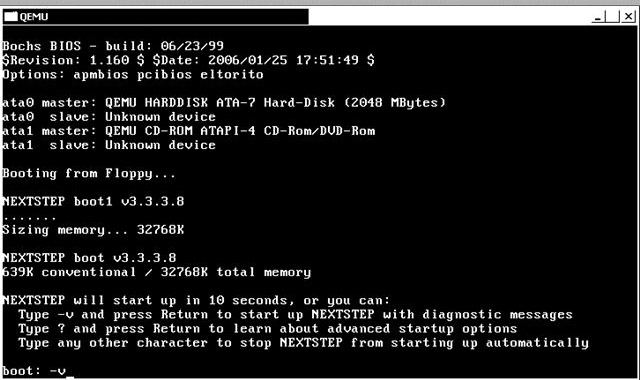
Systemschrift NeXT
Das Problem bei solchen vektorisierten Pixelschriften, dass die Pixel eben fast nie auf Bildschirmpixel fallen und durch fast immer fehlendes, und bei soler Schriftart recht kompliziertes Hinting dann auf dem Bildschirm grausam aussehen, werden sie nicht sehr groß dargestellt.
Das hier ist die Schrift der Oberfläche:
, ich suche jedoch eigentlich die Schrift, die bei einer kernel panic angezeigt wird wird bzw. beim Hochlaufen und Herunterfahren. Oder ist das bei Mac OS X vor Maverick immer noch die gleiche geblieben?
P.S.: Ich habe mal Mac OS X im »Verbose mode« hochgefahren. Es ist in der Tat dieselbe Pixelschrift, wie NeXT sie verwendet hat.
Ich fürchte, da wirst du kaum Erfolg haben.
In dem abgebildeten Terminal-fenster handelt es sich um eine 5 x 10 Pixel Schrift. In diesem Raster ist natürlich für eine lesbare Schrift nicht all zu viel Gestaltungs-Freiraum, daher wird die auch kaum einen Namen haben.
Generell sind Pixelfonts ja bei gringer Auflösung und auch einem Röhrenmonitor, der problemlos jede Auflösung darstellen kann ja unschlagbar. Bei LCD-Monitoren, die ja prinzipbedingt Pixel (aus je einem RGB-Tripel) besitzen, relativiert sich dieser Vorteil wieder deutlich, da ja hier eine niedrige Auflösung der System-Nur-Text-Ausgabe auf die Bildschirmpixel neu abgetastet werden müssen. Das übernimmt dann wieder ein Grafikprozessor auf dem Mainboard des Bildschirms, und die machen oft ziemlichen Murks aus einem Pixelfont, drum sind viele Betriebssysteme dazu übergegangen, auch bei Systemmeldungen (Bluescreen, Kernal-Panic, Ladebestätigungen für Softwaremudule und Gerätetreiber bei Linux) und in Terminal-/Eingabeaufforderungs-Fenstern auch Vektorschriften zu verwenden.
Zwar ist in Windows10 noch immer ein recht breites Sortiment an Pixelschriften installiert, in einer realen Anwendung habe ich sie jedoch nicht mehr gesehen. Möglich, dass hier das System den Bildschirm erkennt, und diese nur auf Röhrenbildschirmen nutzt.
Vektorisierte Pixelschriften sind jedoch ein Anachonismus, und sind außer in "Digital-historisierenden" Dokumenten praktisch schlechter in der Bildschirmdarstellung als Vektorfonts mit wenigen Ankern und glatten Konturen, die sich deutlich besser auf die native Bildschirmauflösung rendern lassen, Besonders, wenn anständige Hints zur Verfügung stehen.
Zwar ist in Windows10 noch immer ein recht breites Sortiment an Pixelschriften installiert, in einer realen Anwendung habe ich sie jedoch nicht mehr gesehen. Möglich, daß hier das System den Bildschirm erkennt, und diese nur auf Röhrenbildschirmen nutzt.
Wahrscheinlich sind diese nur deshalb noch installiert, damit falls ein älteres Programm danach verlangt sie noch vorhanden sind.
Ein älteres Programm wie z.B. das OS?
Also, das hier hier ist ein Foto vom Bootvorgang einer NeXT. Und *diese* Schrift habe ich gesucht.
@ catfonts: Es gibt keine »vektorisierten Pixelschriften.«. Die Entwicklung, war von Vektoren über Bézierkurven und dann idiotischerweise quadratische Q-Splines (TrueType).
Ich gebe offen zu, dass ich der Meinung bin, man hätte die Entwicklung von TrueType ja auch einstellen können, nachdem klar geworden war, dass die funktionale Einheit von Darstellung und Ausgabe eben einfach am Mac überlegen ist, nur kostet das denn auch seinen Preis.
(((Ich Vollidiot habe meinen Plattenspieler, immerhin ein rega planar 3, und einen Teil der Schallplattensammlung.verkauft. Wie konnte ich das nur tun?)))
Aber zurück zum Thema: Hier ist der Font im Original. Selbstverständlich eine Pixelschrift, weil die grafische Oberfläche mit ihren Umrissbeschreibungen noch gar nicht geladen ist.
@ Ralf:
Ich wüsste ja auch gar nicht, warum ich mich um eingesetztes Material, Konstruktion & Leistung eines Trabbi scheren sollte, bevorzuge ich es doch, per Taxi zur Dialyse und zurück in einen Mercedes-Benz zu fahren. SCNR!   :-)    :bandit:    :tutor:
Und zum Thema »Nachhilfe TrueType« ist mir der Zugang auf Grund des Knochens, der mir dabei quer im Hals hängt, leider verwehrt. Apple & M$ in schönster Eintracht gegen Adobe …
@ catfonts:
Aber erkläre doch einmal, was Du mit den »vektorisierten Pixelschriften« überhaupt gemeint hast. Und verzeih’, wenn ich Dich etwas unzart angefasst haben sollte. Und ich selbst erinnere mich gerade an ein über die erlaubte Größe ausgegebenes Beispielwort, das unser Berufsschullehrer testweise einmal auf der Linotronic 300, einem der ersten CRT-Belichter, ausgegeben hatte und wo man die Vektoren klar erkennen konnte.
Oder meinst Du das, was mit der »Chicago« lange Zeit bei Apple gemacht wurde? Eine Pixelvariante für die Monitore, PostScriptkurven für die Printer?
@ Lars Schwarz: Ich habe nicht verstanden, worauf Du mich mit dem Link hinweisen wolltest.